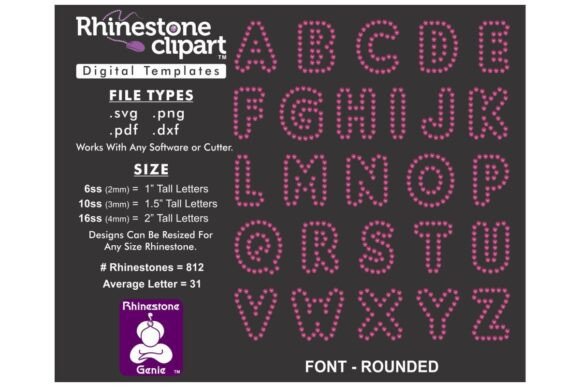
Rhinestone Design FONT - ROUNDED 1.5"
Việc tìm kiếm các thành phần thiết kế phù hợp có thể là một thách thức, nhưng Rhinestone Design FONT - ROUNDED 1.5" cung cấp một bộ sưu tập đặc biệt giúp nâng tầm công việc của bạn ngay lập tức.